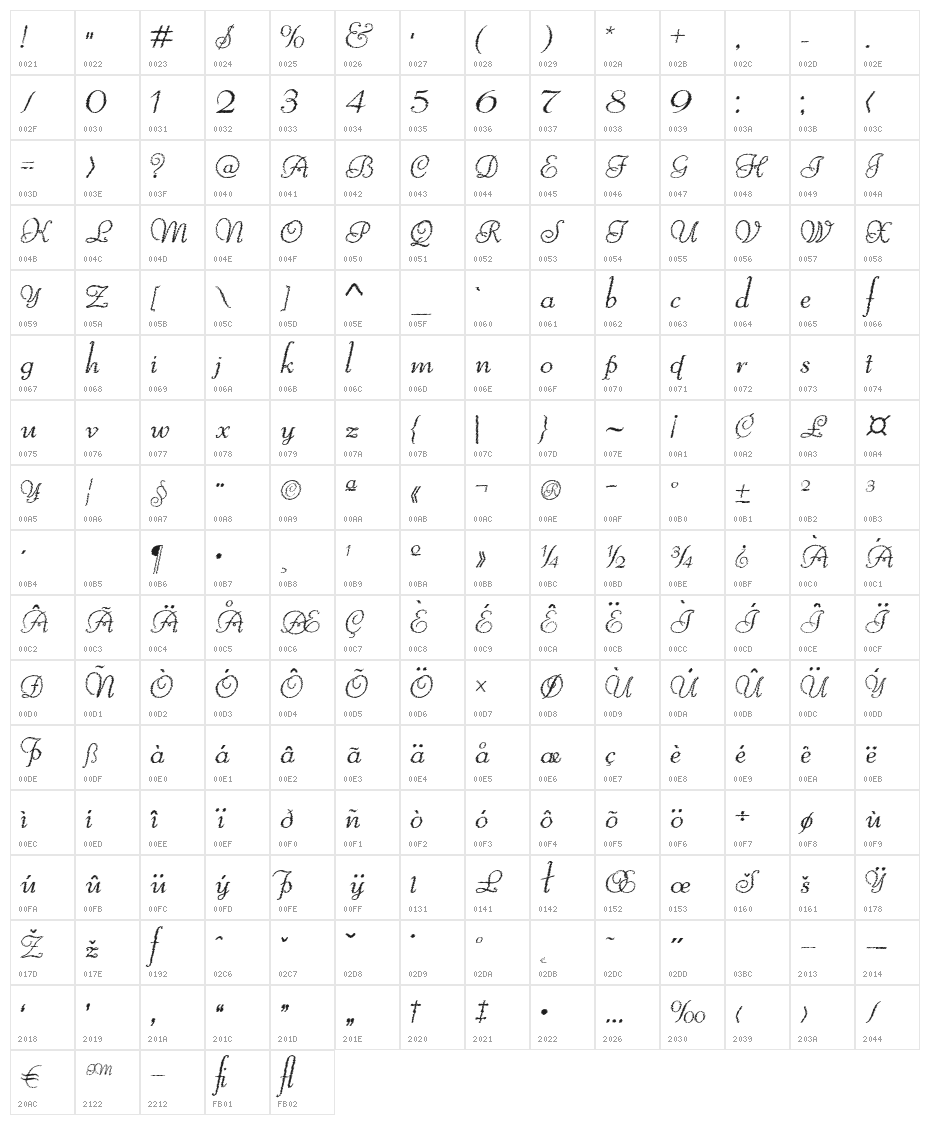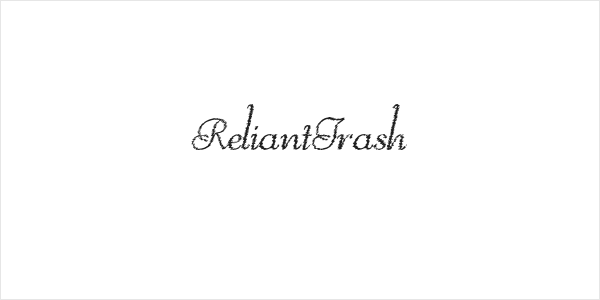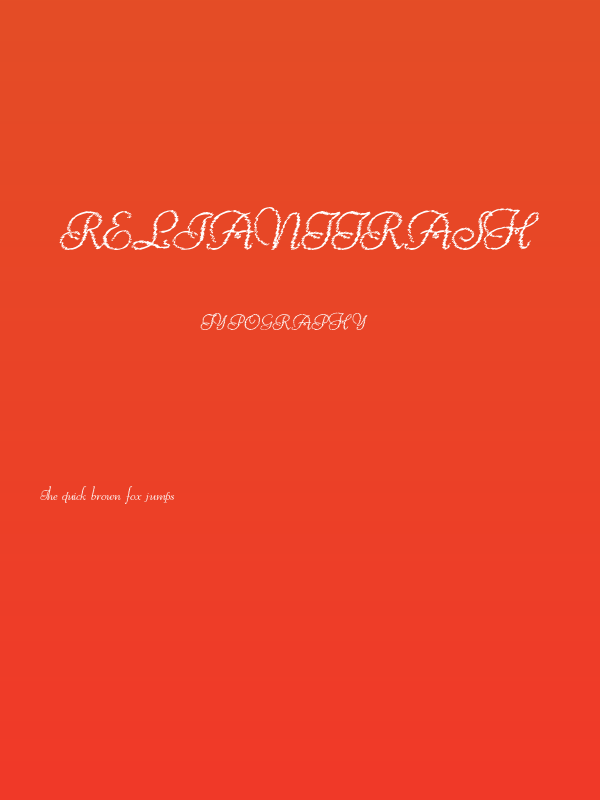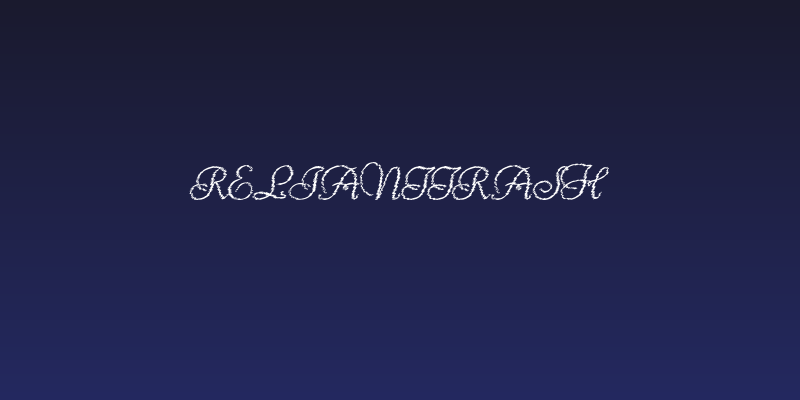
ReliantTrash Font
✎ Script
| श्रेणियाँ | Script |
| इटैलिक | Yes |
| समग्र शैली | Decorative |
| उपयोग का मामला | Logos, Invitations, Artistic projects |
| सुझाए गए प्रोजेक्ट | Ideal for wedding invitations, greeting cards, artistic posters, and branding materials that require a personal and elegant touch. |